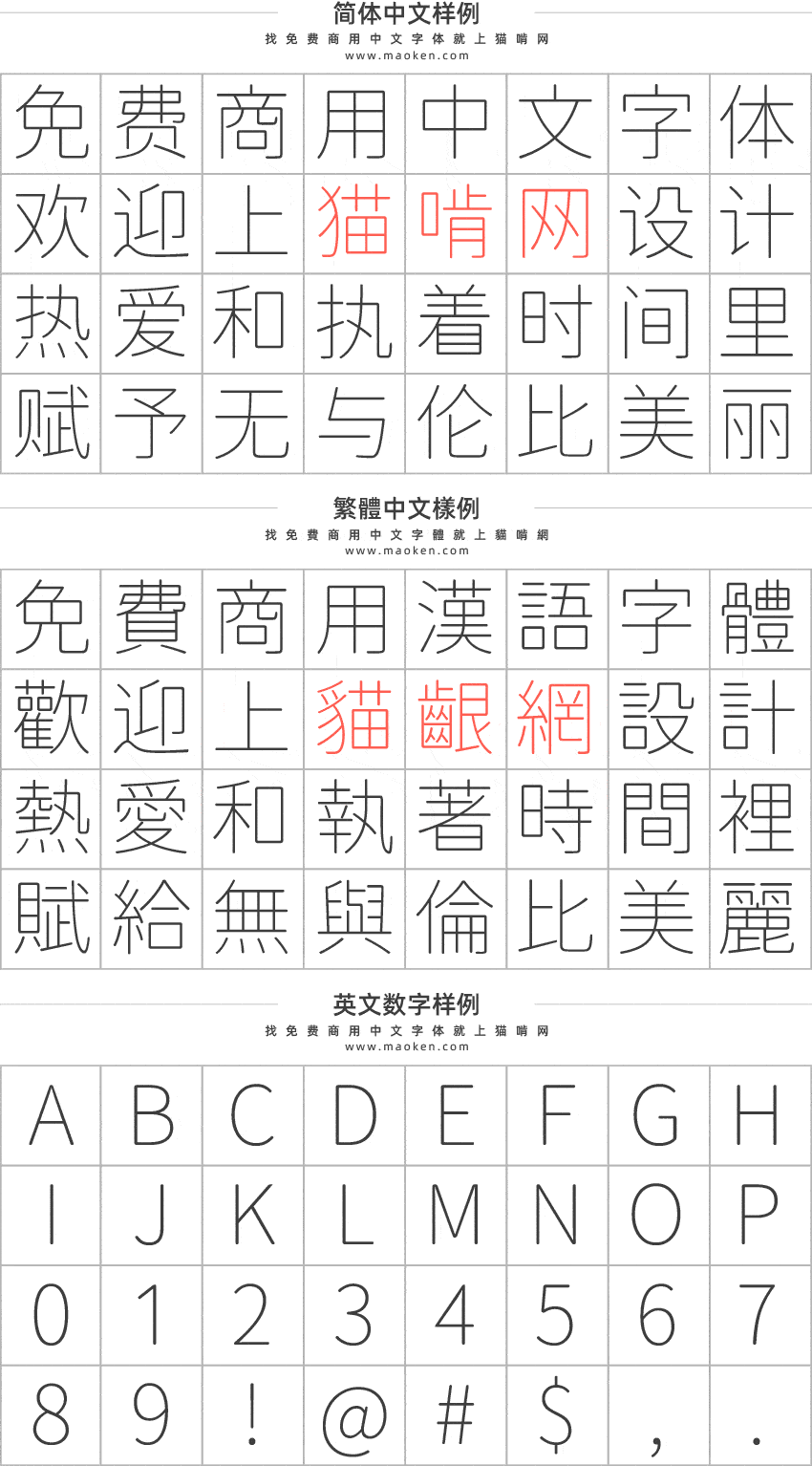
江城圆体:终于有一款比较适合国内设计师使用的圆体字形了
字体作者:刘鹏 (中国大陆) 字体字重:6个
猫啃网之前一直觉得没有一款比较适合的可以免费商用的圆体字形。在搜集免费商用中文字体的过程中,发觉大部分的文章都介绍使用“思源柔黑体”,后来我发表了一篇文章《源柔黑体:日本自家製フォント工房改造的思源字体》为“思源柔黑体”正名。因为这款字体应该叫“源柔黑体”而不应该叫“思源柔黑体”,具体原因大家可以看一下源柔黑体那篇文章。
猫啃网那时建议大家使用源泉圆体或资源圆体替换掉网上一直流传的“思源柔黑体“,但是这两款字体对于中国大陆的设计师来说依然有点小瑕疵。源泉圆体因为是台湾设计师改造的字体,所以字形上会更贴近中国台湾的使用习惯。比如源泉圆体某些字的写法还是台版字形,而资源圆体则是思源黑体的直接变圆版,字形上保留着黑脚,看上去还是比较像黑体。
终于本站网友,一位被设计耽误的程序大神刘鹏,基于源泉圆体进行改造,把一些台湾习惯的字形进行简体化修正,发布了一款比较适合我们大陆设计师使用的字体”江城圆体“。这款字体基本源泉圆体改造,所以简体也是不缺少字的。并且有6个字重,十分贴心。猫啃网建议大陆的设计师们,可以把电脑上的源泉圆体删掉,替换成这款江城圆体吧!!江城圆体改过的字可以点击这里查看。
Ver 3.6(2021/10/22)
• 修改 僔噂墫嶟撙樽竴罇蹲鐏鱒
• 修改 冢啄涿椓琢塚瘃硺諑
• 优化了部分字形
Ver 3.4(2021/04/28)
• 修改了约439个字X5个字重
Ver 3.3(2021/02/21)
• 江城圆体更新3.3版本
• 修复了竖排文字会有叠加bug
• 西文字母及数字选用Baloo2
• 删掉了200W字重,全新为5个字重
• 修改了网友反馈的与常规写法有异的字
Ver 3.1(2020/10/13)
• 江城圆体更新3.1版本
• 修改了网友反馈的与常规写法有异的字
• 修改了包含“半”“肖”“力”“亡”“亥”“幺”“免”部件构形的异体字共计325个字
Ver 3.0(2020/08/20)
• 江城圆体更新3.0版本
• 修改了约115个与常规写法有异的字体(6个字重)改过的字可以点击这里查看。
• 拔掉了700W字重下带“口”旁的字脚约49个字 改过的字可以点击这里查看。
Ver 2.5(2020.07.15)
• 江城圆体更新2.5版本
• 修改了约135个与常规写法有异的字体(6个字重)改过的字可以点击这里查看。
• 拔掉了700W字重下啃、和、时等字脚。
Ver 2.0(2020.06.14)
• 江城圆体更新2.0版本,这个版本修改了约50个与常规写法有异的字体,改过的字可以点击这里查看。
Ver 1.5(2020.06.10)
• 江城圆体更新1.5版本,这个版本继续对部分字进行修改,改过的字可以点击这里查看。
Ver 1.0(2020.06.09)
• 江城圆体正式发布。江城圆体改过的字可以点击这里查看。